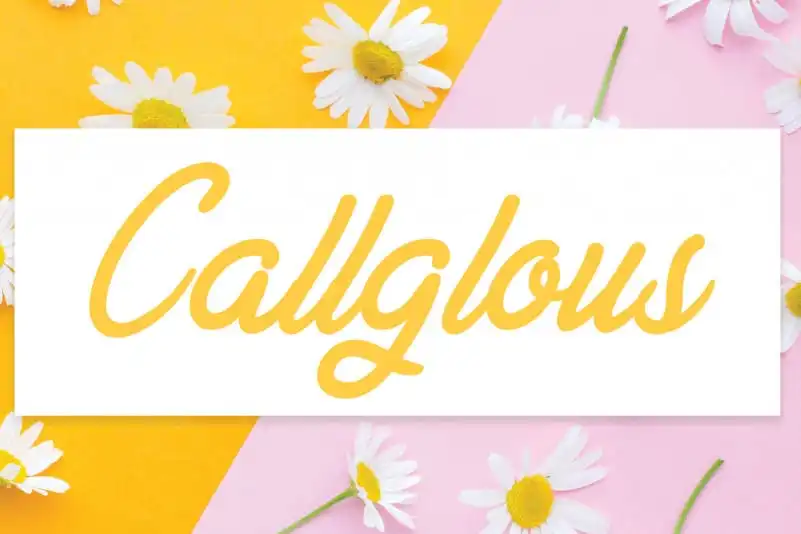
Callglous Script Font – Download Grátis
A Callglous Script Font é uma mão-d escrita única e sofisticada, perfeita para adicionar um toque criativo a seus projetos digitais. Escrevendo diretamente com sua caneta, o designer andikastudio criou esse charmoso conjunto de caracteres que vai transformar seu conteúdo em algo realmente especial. Com traços elegantes e detalhes meticulosamente executados, essa fonte é ideal para aqueles que buscam uma maneira única de expressar a essência do design gráfico. Se você está procurando por uma fonte que possa fazer sua identidade visual soar ainda mais distintiva, a Callglous Script Font pode ser exatamente o que você precisa. Combinada com outros recursos digitais como imagens e cores vibrantes, essa fonte vai garantir que seu trabalho seja notado e recordado por muitos anos. Seja para aplicativos de design gráfico ou publicidade digital, a Callglous Script Font oferece uma maneira única de incorporar um estilo autêntico em qualquer projeto. Através de sua versatilidade e facilidade de uso, essa fonte vai transformá-lo em um criador ainda mais expressivo e original.